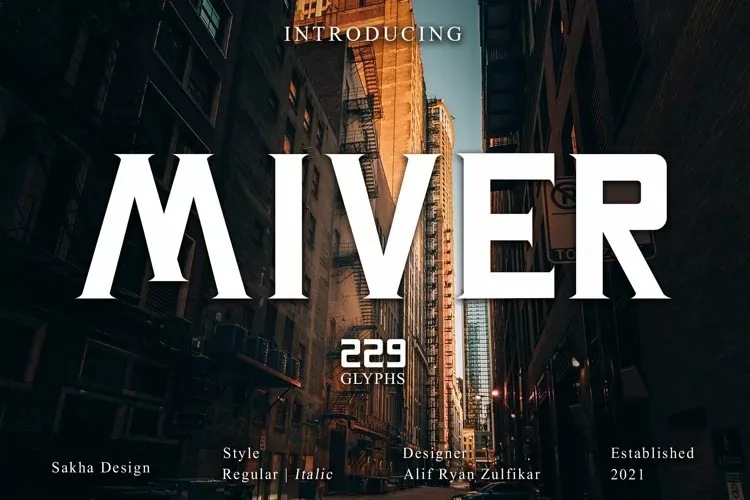
A Miver Font é uma elegante escolha para designers que buscam um tipo serif para trabalhos visuais impactantes. Ela surge do talentoso designer Sakha Design e traz um toque sofisticado à sua biblioteca de fontes. Confortável para uso em cabeçalhos, títulos de painéis, logotipos, sinalização e embalagens, a Miver é uma escolha perfeita para criar texturas impressionantes e personalizadas. Se você está buscando um tipo que pode dar um toque final a qualquer projeto gráfico, a Miver certamente será uma excelente adição à sua coletânea de fontes. Essa elegante serif traz leveza e profundidade ao seu trabalho, ajudando-o a destacar em qualquer plataforma digital ou impressa. Com seu design minimalista mas caracterizado por traços finos e bem projetados, a Miver é uma excelente escolha para quem quer dar um toque sofisticado e moderno às suas criações visuais.